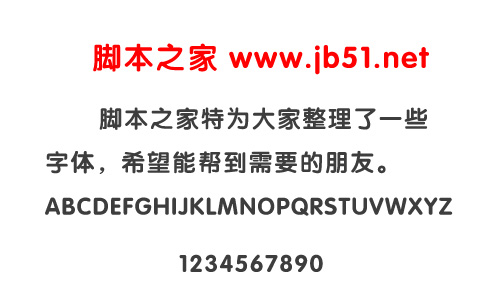
方正粗圓簡體字體是方正字體庫中的一種字體,方正圓體家族的中宮寬松,字面大,起筆處與收筆處為圓形,折筆處呈圓弧狀。方正圓體家族的字形風格舒展柔和,適用于女性、兒童和生活用品類的宣傳冊和包裝設(shè)計等。方正圓體家族包括3款字重,其中方正粗圓筆畫厚重飽滿,適用于標題;方正準圓筆畫粗細適中,適用于正文排版;方正細圓筆畫纖柔,也適用于正文排版。喜歡的朋友們可以前來下載使用。